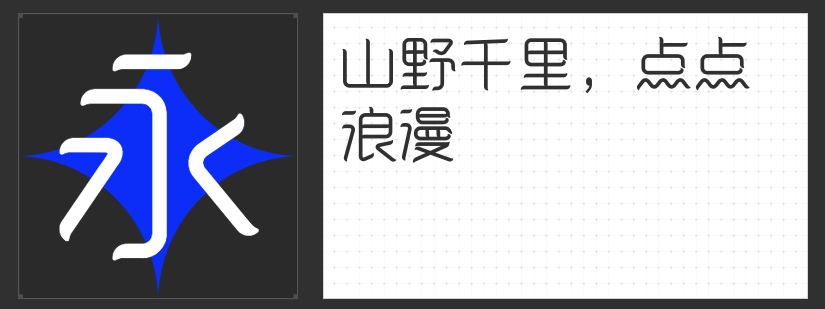
四款风格化字库字体推荐:为LOGO设计注入独特灵魂
在LOGO设计中,字体不仅是品牌信息的载体,更是视觉识别的核心符号。一款契合品牌气质的字体,能在瞬间传递调性、建立情感连接。以下四款字库字体,以鲜明的风格化特征与专业设计细节,为LOGO创作提供多元灵感。
一、造字侠侠义简繁
这款字体以「潇洒狂放」为底色,却通过「端正平稳」的结构化解了潦草感,形成动静相宜的张力。其笔画以圆转替代方折,勾挑牵丝的细节强化了字与字之间的呼应,仿佛墨迹在纸上自然流淌。这种设计既保留了书法的写意性,又通过严谨的布局确保了远距离识别的清晰度,适合追求文化底蕴与艺术感的品牌,尤其是传统行业革新或国潮类LOGO。
二、励字勇敢黑简 大黑
作为无衬线字体的代表,励字勇敢黑简以「粗壮有力」的笔画和「横直均匀」的结构,构建出强烈的视觉冲击力。撇捺笔画的钝化处理消除了尖锐感,既提升了阅读舒适度,又传递出稳重可靠的印象。其醒目却不张扬的特质,使其成为科技、运动、工业类品牌LOGO的理想选择——既能快速抓住注意力,又能经得起时间考验。
三、高手庆科雅韵体
这款字体的设计语言围绕「和谐」展开:中宫略大、布白均匀的布局赋予其呼吸感;横竖笔画等粗的视觉处理,搭配微翘的笔形与简化的钩画,在克制中透出灵动。西文符号与中文的「圆润+断开」统一设计,解决了中英混排时的风格割裂问题。其优雅而不失现代感的特质,适合高端零售、文化创意或生活方式类品牌,传递精致与温度并存的调性。
四、励字山中精灵简
以「圆润可爱」为核心,这款字体通过饱满的笔画、留白空间与拙朴的转折,塑造出童稚般的亲和力。萌动的视觉语言却未牺牲实用性——清晰的字形结构与均匀的布白,确保了小尺寸下的可读性。其「二次元与三次元通吃」的特质,既能适配儿童品牌、文创IP,也能为年轻化品牌注入轻松趣味,成为打破刻板印象的利器。
LOGO字体选择需兼顾「风格匹配度」与「应用场景」。若品牌强调文化传承,可优先考虑书法变体;若需传递现代感,无衬线或几何字体更稳妥;而儿童或年轻化品牌,则可通过圆润、萌动的设计拉近距离。这四款字体以差异化美学,为LOGO设计提供了丰富的表达维度。